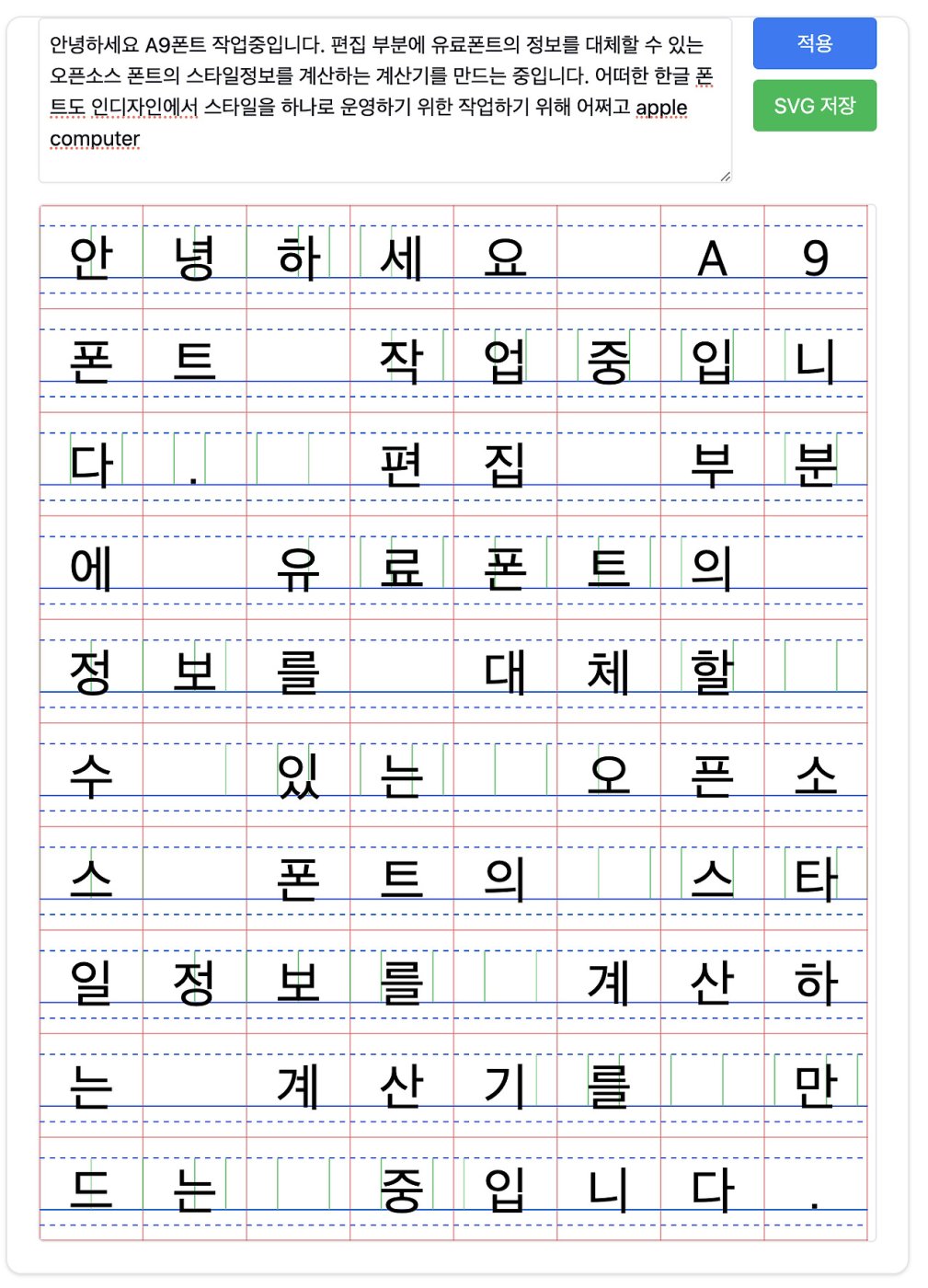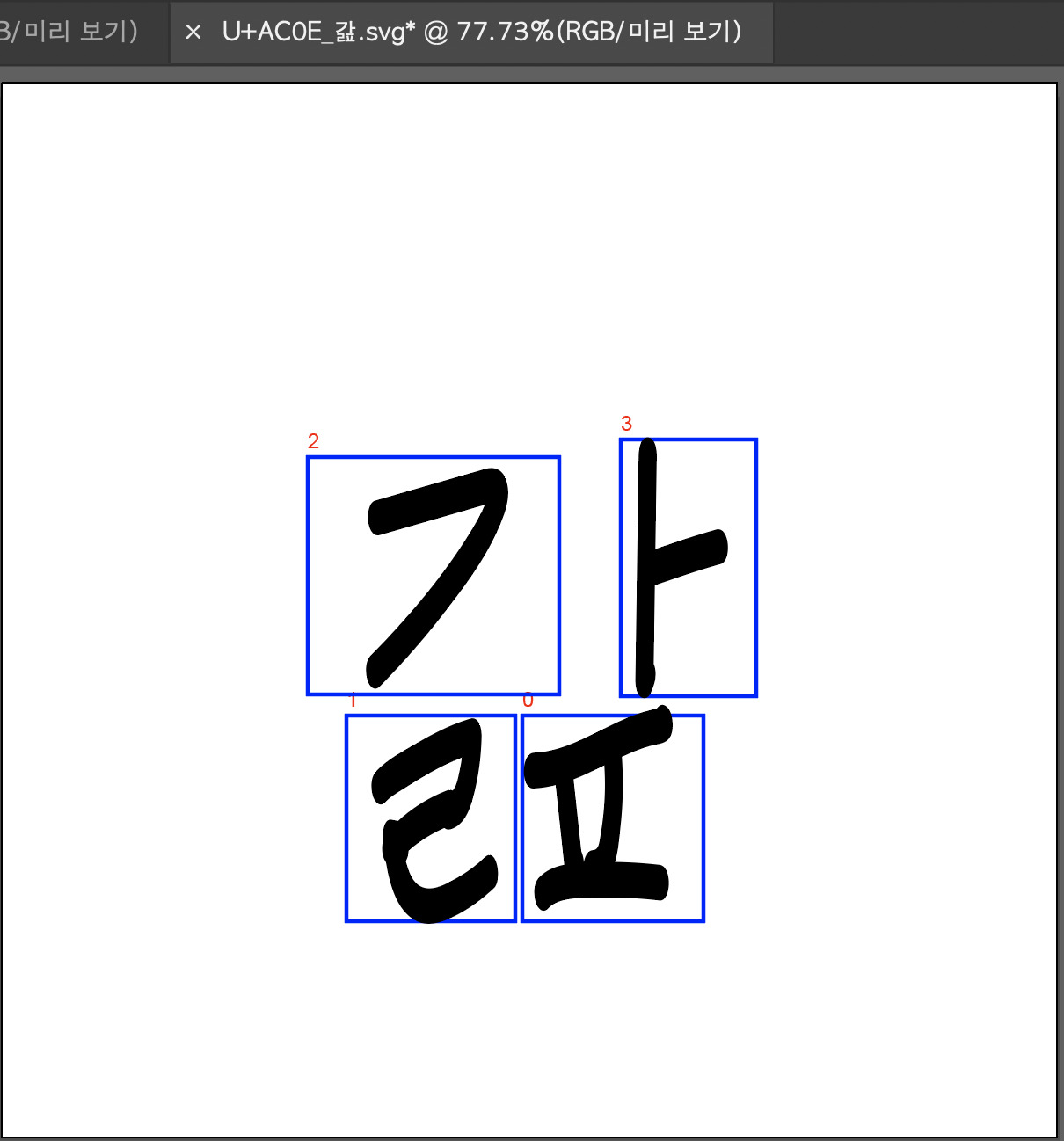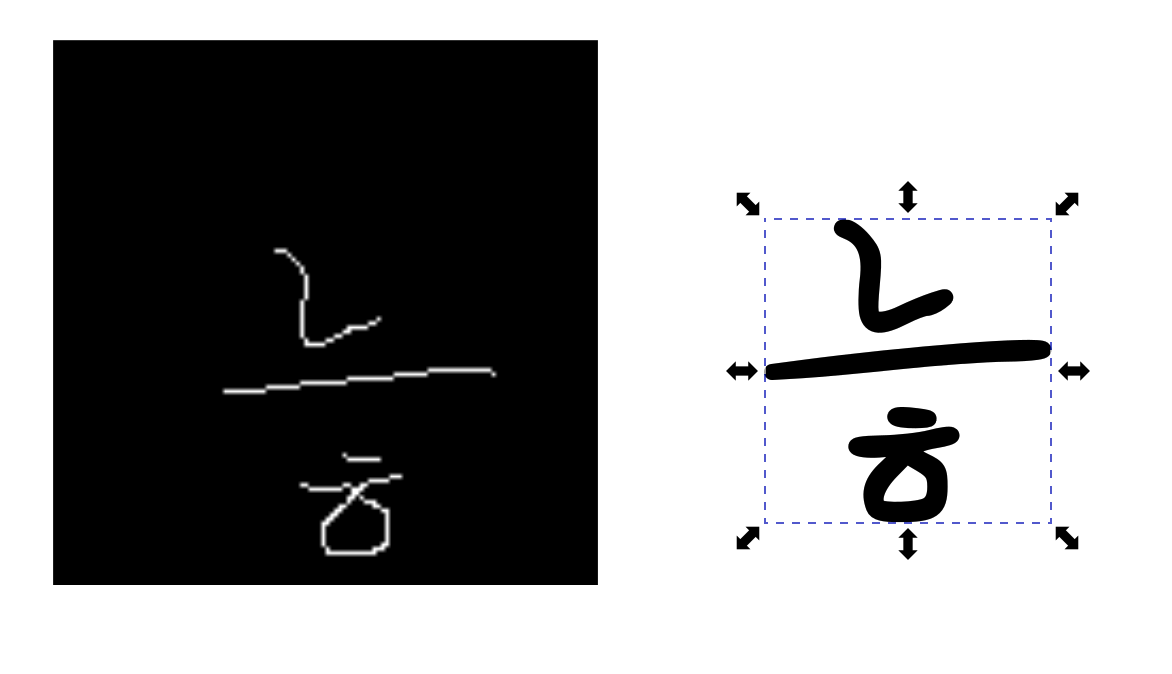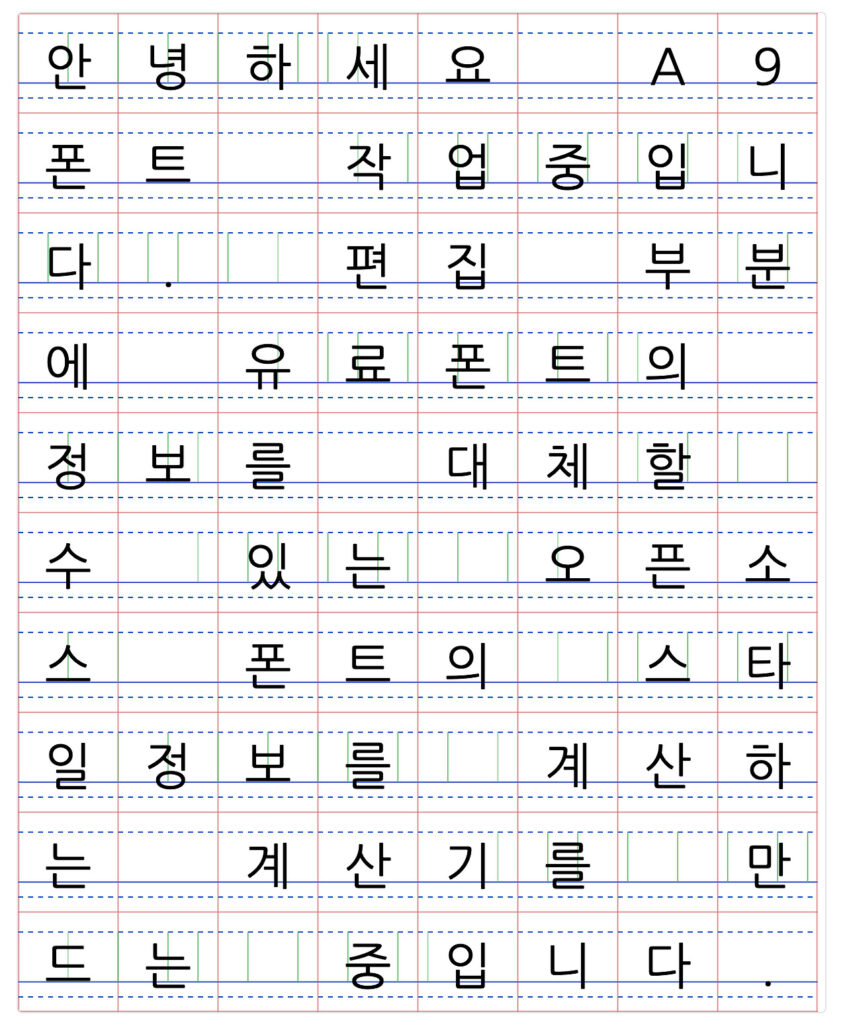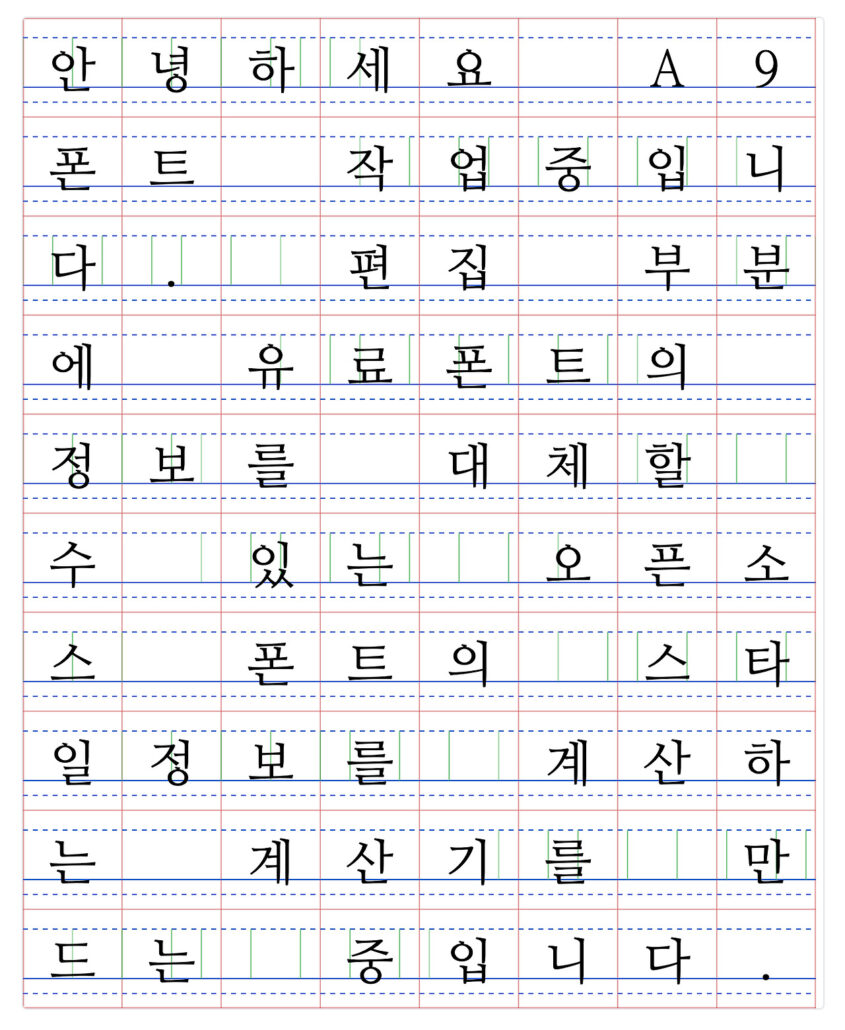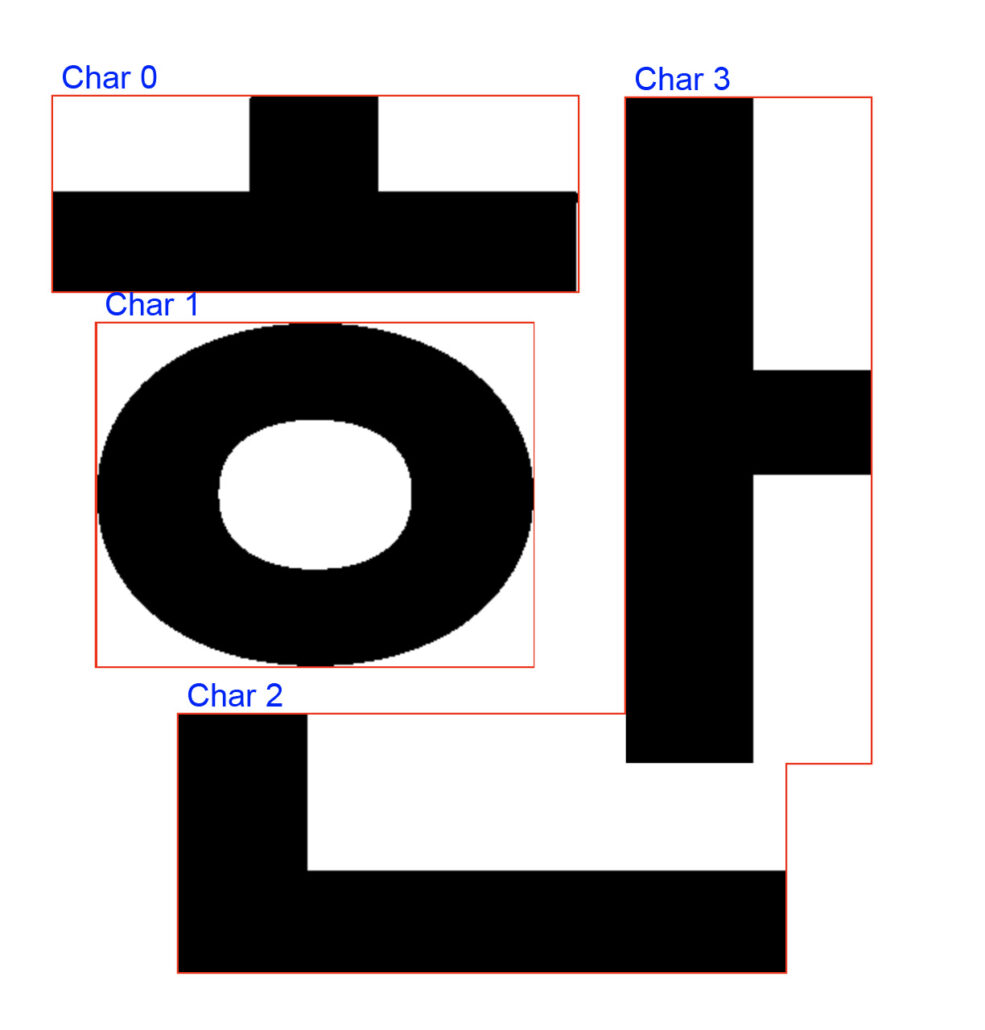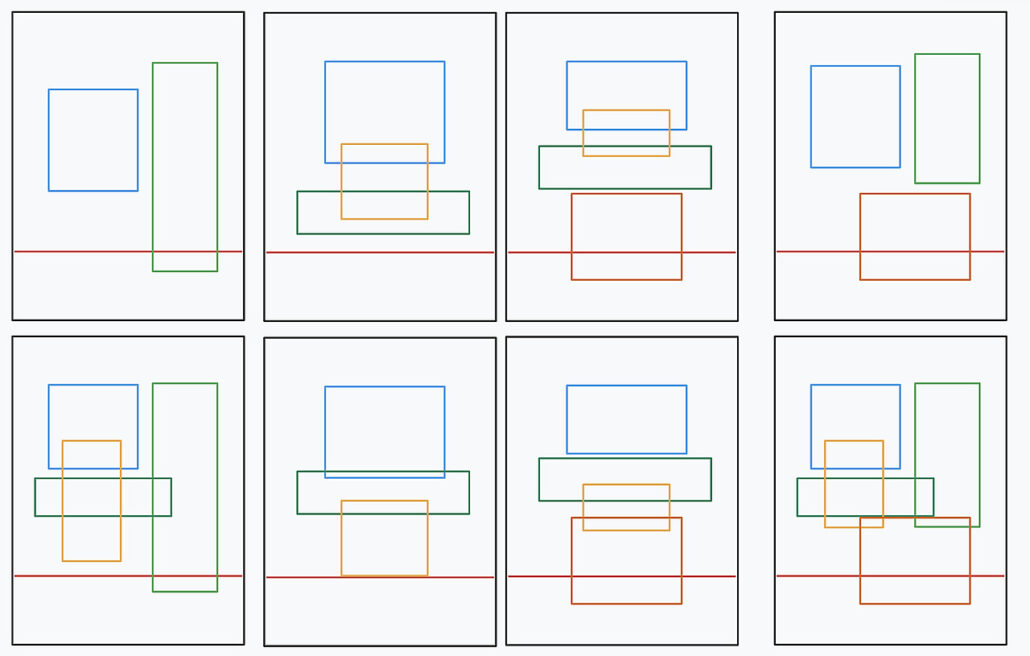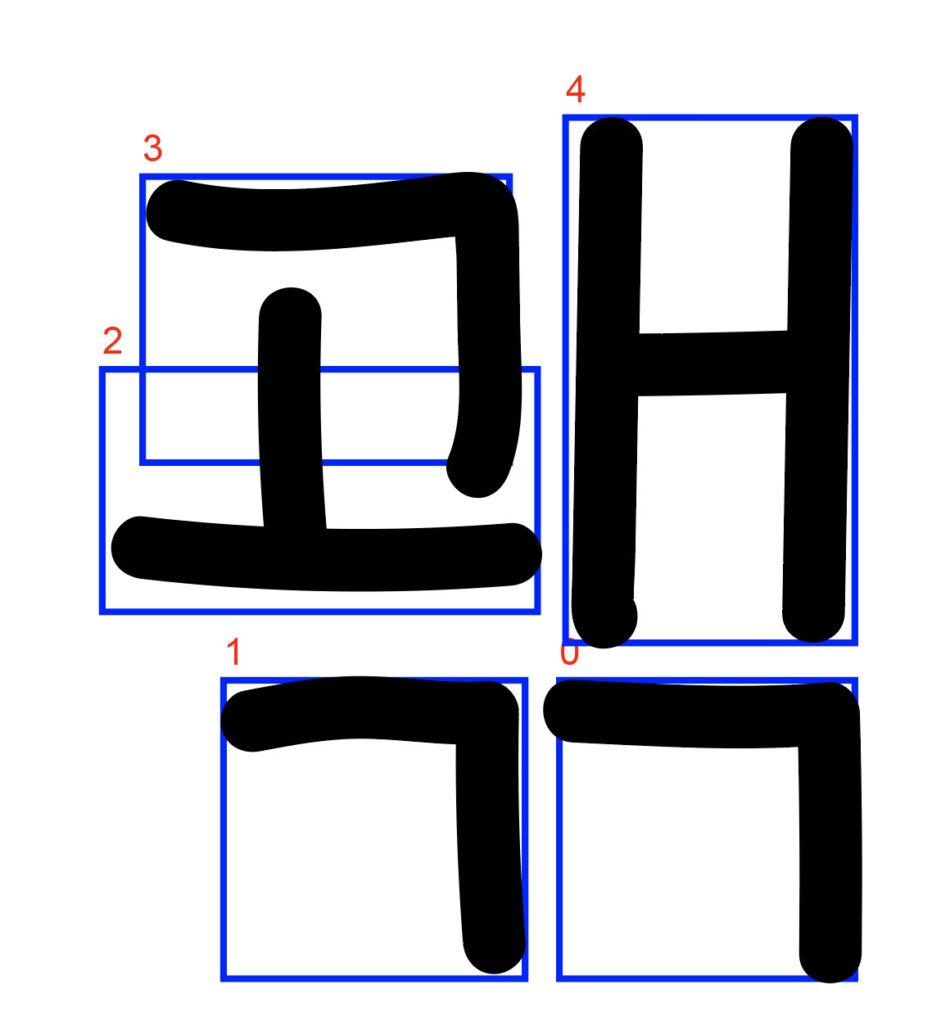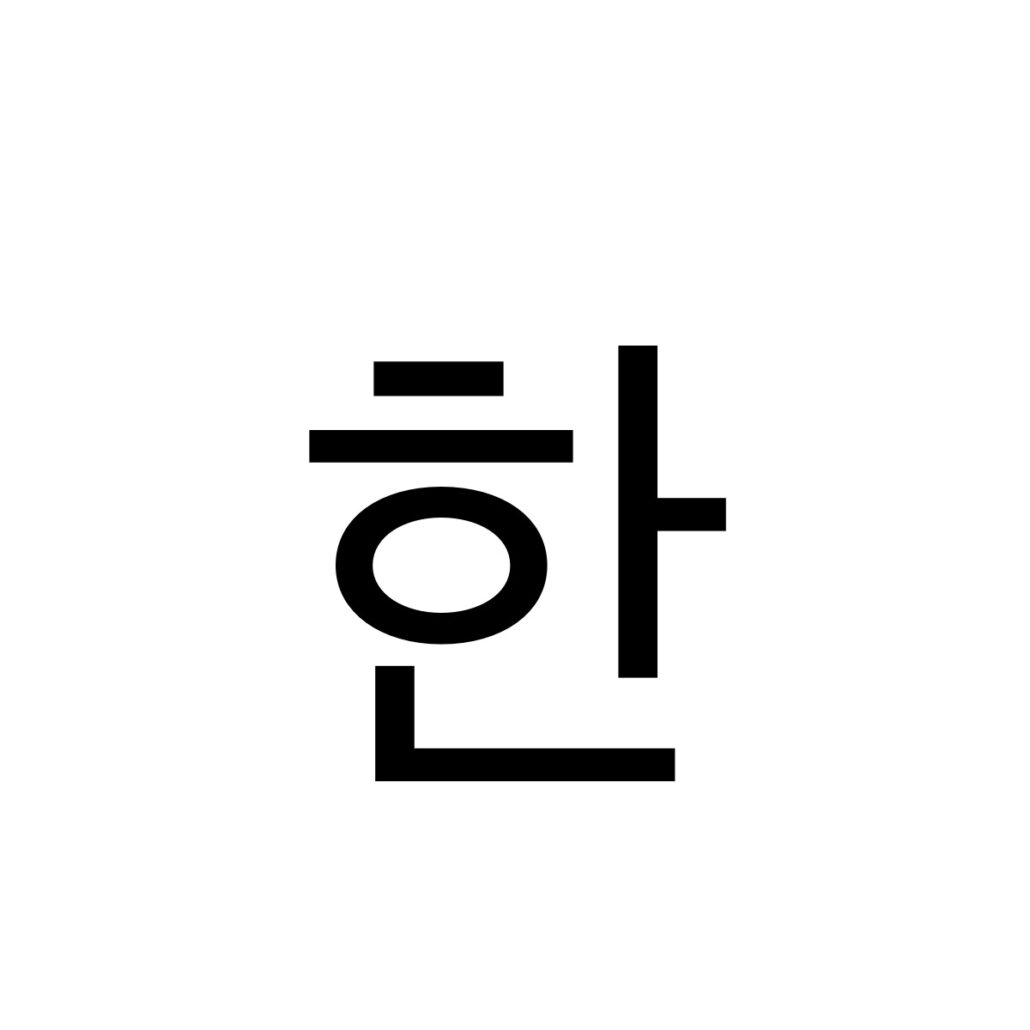
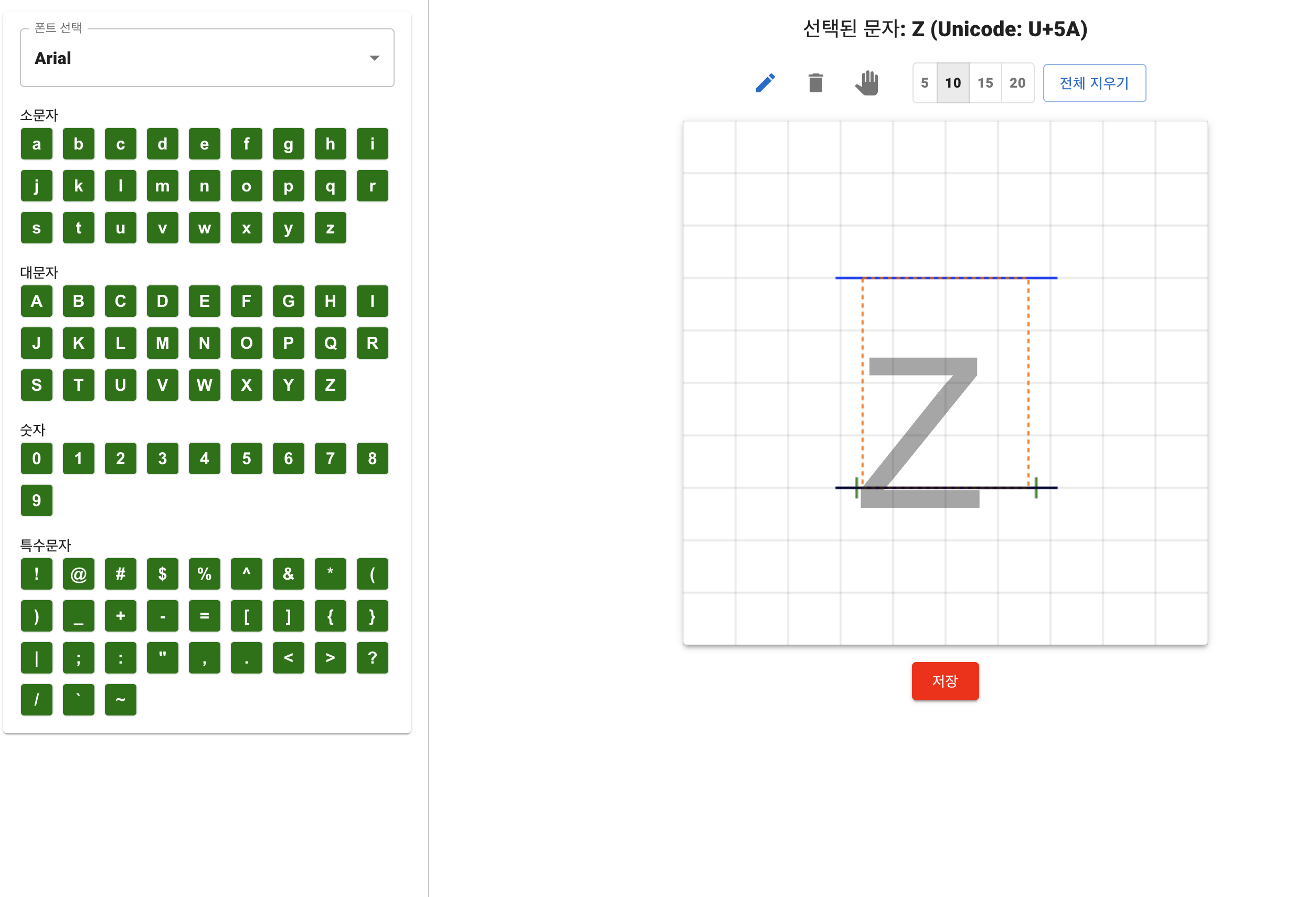대체폰트를 만드는 폰트 편집기
A라는 유료폰트를 B라는 폰트가 대체
아주 오랫동안 고민했고 폰트의 쓸모를 만들기 위해 지난 2년여 기간 동안 어떤 콘셉트에 맞춰 여러 가지 프로그램을 해봤습니다.
폰트에디터를 만드는 것은 어쩌면 쉬울 수 있습니다.
폰트를 리버스 엔지니어링을 통해 만드는 것은 사실 쉽습니다. 왜냐면 폰트는 기본적으로 공개된 정보를 제공하기 때문이며 영문은 메트릭이나 여러 가지 정보를 볼 수 있습니다.
그래서 대체폰트가 많이 있습니다. 대체할 수 있는 비슷한 폰트가 아주 많아요. 그런데 한글은 대체할 수 있는 폰트를 만들기 어렵습니다. 지난 2년간 대체폰트에 대해서 고민을 아주 많이 했습니다.
인디자인을 쓰다 보면 A라는 유료폰트를 전자책을 만들게 될 때 문제가 발생합니다. 왜냐하면 유료폰트의 일부는 폰트를 전자책에는 제공하지 않기 때문입니다. 그러면 유통사에서는 특정한 무료폰트를 지정해서 만들게 하는데 그걸 쓰면 디자인이 다 일그러집니다.
그 문제를 해결하고자 A라는 폰트의 커닝, 스타일을 전자책용으로 다시 재구성해서 만드는 프로그램을 하고 있었는데 본질적인 문제를 해결하는 게 오히려 더 쉽다고 판단해서 폰트를 대체하는 폰트를 만들기로 했습니다.
손글씨로 폰트를 만드는 일이 생각보다 안 풀려서 한동안 고민하다가 다른 방향으로 이것저것 하다 보니 잠시 잊었는데 오늘 애니메이션 폰트를 추가로 만들다가 다른 폰트의 메트릭을 불러와서 폰트를 생성하는 작업과 복수 컴포넌트를 다시 나눠서 학습하는 부분을 AI가 하게 만들고 대충 마무리했습니다.
결론은 쉽게 만들어집니다. 그래서 이 프로젝트는 닫기로 했습니다.
어쩌면 남의 것을 훔치게 되는 일을 하는 일이라 시간낭비 그만하고 그냥 더 재미있는 것이나 하는 것으로~
2년 걸린 폰트 편집기 작업 마무리중
작년에 만들던 폰트에디터에 대해서 이런저런 고민하다가 3D로 획을 만드는 방법으로 방향을 완전히 틀었고 이제 그 결과물이 거의 끝나갑니다. 그냥 폰트찍어내는 프로그램을 만들기는 했는데 기계에 사용할 폰트를 목적하고 있는 것이라서 조금 다르긴 하지만 하여간 기본 폰트에 대한 부분이랑 한글, 한글 조합 등등 다 좋은데 진짜는…
애니메이션 폰트가 만들어진다는 것 그리고 더 중요한 것은… UFO 폰트 스펙에 다 맞춰서 글자 변형이 자유로워지는 것
만화폰트는 금방 뽑아냅니다. 아이패드 지원도 됩니다. 그리고 템플릿을 기반으로 하는 기능과 몇가지 기능들을 추가중인데 대충 끝나면 폰트 펀딩이나 해야겠어요.
일단 애니메이션 폰트는 영상용이나 방송용으로 쓰일거 같긴한데 그것보다 어르신들 손글씨를 기록하게 될거예요. 이거 만들다 내가 어르신이 된 기분
이건 손글씨폰트지 손글씨라고 하기에는 좀 ^^; 그걸 해결하기 위해서 다른 아이템들을 전부 담아 끝을 낼 예정입니다.
2년 걸린 프로젝트도 이제 거의 끝… 그나저나 인터페이스는 다 바꿔야하는데 디자인은 더 복잡하게 만들어 놓고 간단한 버전을 먼저 만들어서 마무리 했습니다.
한글 폰트에디터 작업이 어느덧 8개월째…
한글폰트 에디터 작업 8개월이 넘어가는 중입니다.
폰트를 모든 컴포넌트로 조합해서 자동으로 조합하는 부분과 타사의 폰트와 완전히 동일한 좌표계를 가진 대체폰트를 위한 에디터입니다. 타사로 바꿔도 같은 자간, 행간 커닝 조합이 되는 것을 하고 있었고 만화쪽 폰트에서 기업용까지 대체할 수 있는 폰트를 만들 목적으로 제작했습니다.
시간이 오래 걸리고 과정도 길고… 한글 폰트는 컴포넌트 방식으로 만들어야 하기 때문에 관련 조합이 상당히 많은 편입니다. 그걸 다 해결할 수는 없고 폰트형태에 따라 달라지게 됩니다.
그걸 가이드별로 다르게 처리하는데 일단 전문 폰트 에디터들이 한글용으로 기준을 잡아 만들고 있지 않으니까 이것저것 작업해야 할게 많아집니다. 그래서 옛날에 만든 폰트중에 3000개 내외의 글립스를 가진 폰트가 많아서 그걸 인쇄용으로 쓰려면 포기하고 새로 다른 본문용을 선택하는 경우가 많습니다. 현재 새로 조합해서 만들고 수정을 해야 하는 부분이 있지만 저희는 틈새를 노리는 에디터입니다.
### 컴포넌트 라이브러리 – 자주 사용하는 자모 부분을 라이브러리에 저장 – 카테고리별로 컴포넌트 관리 (초성, 중성, 종성, 사용자 정의) – 드래그 앤 드롭으로 컴포넌트 배치 – 더블 클릭으로 컴포넌트 즉시 추가 – “현재 선택 저장” 버튼으로 새 컴포넌트 추가
1. **문자 선택**: 편집할 한글 문자 입력 2. **자모 확인**: 초성/중성/종성 구성 확인 3. **레이아웃 설정**: 자동으로 설정된 자모 레이아웃 확인 4. **컴포넌트 배치**: 라이브러리에서 기본 형태 배치 5. **세부 조정**: 베지에 도구로 세부 형태 조정 6. **일관성 검토**: 글리프 네비게이터로 다른 문자와 비교 7. **저장**: 완성된 문자를 JSON 형식으로 저장
현재 수정중인 에디터 부분은 면 기반이 아니라 선기반으로 작업중입니다. 끝
뇌 건강을 감지하는 3D손글씨 프로젝트
손글씨 프로젝트의 다음단계
3차원 공간에서 글자를 만들 생각을 하고 있습니다. 이 생각은 폰트를 만들면서 계속 고민한 부분인데 획을 모두 각도별로 따로 Depth 별로 구분하고 랜더링해서 glyph 를 만들어서 구성하는 것입니다.
그러면 각기 다른 각도의 폰트는 물론 사람 특유의 서체를 구현할 수 있으리라 봅니다. 특히 획의 힘주는 포인트를 압력을 Depth 로 구분하면 제가 맨 처음에 폰트를 만들려고 했던 기계가 인간을 온전히 따라하는 장비에 맞는 폰트를 구성할 수 있습니다.
가시적으로 보여지는 것이 외에 데이터기반으로 압력감지를 폰트화 하는 것이라서 보일때는 2D인데 실제로 전혀 다른 데이터가 포함된 필기를 건강이랑 결합한 프로젝트입니다. 인간의 노화도 알아볼 수 있고 ? 필체의 변화를 건강상태랑 즉각 반영합니다. 특히 뇌에 이상이 생기면 필기체가 변화합니다.
이건 저도 경험한바 있기때문에 인지기능을 테스트하는 것과 비슷합니다. 같은 글씨를 매년 쓰면 다른 글자가 나오게 됩니다. 그걸 이용한 프로젝트입니다.
신경학적 변화 감지
파킨슨병, 알츠하이머 등 신경퇴행성 질환의 초기 징후 포착
뇌졸중 후 회복 과정 모니터링
미세한 운동 기능의 변화 추적
데이터 수집 방식
필기 압력 (pressure sensitivity)
글자 모양의 일관성
쓰기 속도와 리듬
획의 연속성과 끊어짐
실시간 건강 모니터링
정기적인 필기 샘플 수집을 통한 변화 추적
갑작스러운 변화 발생시 조기 경고 시스템
장기적인 건강 트렌드 분석
이런 시스템을 구현하기 위해서는 다음과 같은 기술적 요소들이 필요할 것 같습니다:
압력 감지 센서
실시간 데이터 처리 알고리즘
머신러닝 기반 패턴 인식
시계열 데이터 분석
와콤, 아이패드만 있으면 감지가 됩니다. 그리고 지속적인 손글씨 연습데이터를 기록하는 앱을 준비하고 있습니다. 그 것을 이용해서 폰트도 만들어 드릴 생각이지만 본 목적은 향후 본인의 글씨를 교정하는 것도 있지만 내가 어떤 글씨를 쓰고 있고 건강에 문제가 발생했을 때 미리 알아 차릴 수 있게 하는 것도 있습니다.
Wacom의 압력감지:
압력 레벨의 정밀한 감지 (대부분의 모델이 8192단계)
펜의 기울기 정보도 활용 가능
실시간 데이터 스트림 접근 가능
아이패드 애플펜슬의 압력감지
압력감지 특성
최대 4096단계의 압력감지
기울기(Tilt) 감지 가능
방향(Azimuth) 데이터 수집
초당 240회 데이터 샘플링
Web API 접근
제가 폰트를 만드는 이유도 CNC, 로봇팔 등에 인간 고유의 것을 접목하려는 것도 다 연결되어 있습니다. 뇌졸중이 온지 벌써 8년째인데 제가 느낀 것은 현재 손상된 부분은 연습을 통해 매꿔질 수 있지만 본질적으로 우회하고 있다는 것입니다.
이 프로젝트는 매번 쓰는 글자를 통해 스스로 변화를 감지하기 위함입니다.
bone 폰트를 잠깐 개발해서 보고 있습니다.
bone 폰트를 잠깐 개발해서 보고 있습니다. 기존 폰트를 읽어서 뼈대에 해당하는 것을 추출하고 다시 획을 3D애니메이션 할 때 쓰는 bone 을 입혀 한글을 뼈로 만들어서 움직이게 하고 있습니다.
한글서체의 기본 글자의 뼈에 해당하는 중심점을 찾습니다. 스트로크로 폰트만드는 작업을 할 때 필요하기도 하고 현재 가장 문제가 되고 있는 글자를 똑바로 쓰지 않는 손글씨의 원점인 기본 획을 찾아내기 위해 만들었습니다.
구분된 글자를 기준으로 다시 OVAL, Line, Square, 등의 기본 도형에 대한 부분을 추출해서 xml 로 대체할 예정입니다. 바로 전에 만든게 초성, 중성, 종성의 위치값을 찾는 것이라면 이번에는 글씨의 기본인 선의 각도 획의 형태를 찾아내는 것입니다.
두깨는 나중일이지만 일단 이 부분만 중점적으로 학습하고 있습니다.
기계학습을 통해서 조금 고민을 하게 되는 것은 비슷한 알고리즘이 되지 않을까 하는 것입니다. 대신 애니메이션이나 새로운 유형의 글자를 만들 때 재미있는 결과물로 확장할 수 있으리라 생각되기는 합니다. 논문 더 봐야할거 같아요 ^^
아무리 엉망으로 써도 bone 추출후 다시 한글폰트로 만들 수 있습니다. 벡터로 만들어 놓은 것을 감안하면 폰트가 조금 달라지지만 손글씨가 아닌 폰트가 됩니다
레이아웃 자동화 만화효과음 폰트 만들기
주말 다 반납하고 제작한 만화효과음 레이아웃 추출 기능을 대부분 완성했고 반대 작업도 하고 있습니다. 초성, 중성, 종성 한벌만 쓰면 이세상 모든 폰트레이아웃으로 만화효과음 폰트가 그려집니다. 인디자인 대체폰트가 그냥 만들어지기는 하는데 같은 모양이라고 하지 않았습니다. 같은 것도 만들 수는 있지만 일단 그건 예외로 하고
베이스라인 (실선)
x-height 라인 (점선)
어센더 라인 (점선)
디센더 라인 (점선)
중앙 정렬 가이드 (가는 점선)
커닝가이드 그리고 기존 폰트 스타일과 대체 폰트를 x-ray 툴이라는 저희가 만든 폰트 비교 프로그램으로 본문을 기준으로 맞춰보면 눈으로 보이는 것과 기계적으로 분석한 것은 다르기 때문에 비교 결정을 할 수 있게 될 것입니다.
손글씨 하나 폰트로 만들려고 하다가 할 일만 늘어놨네요 ^^
만화효과음 자소 폰트 편집기 프로토타입
웹툰에서 작가고유의 폰트를 만들고 초, 중, 종성을 분리한 콤포넌트를 사용하여 집중선, 퍼스펙티브에 맞춘 글자 레터링을 자유롭게 할 수 있고 폰트패밀리를 사용해서 효과를 즉각적으로 변경해서 확인할 수 있는 폰트를 제작하고 있습니다.